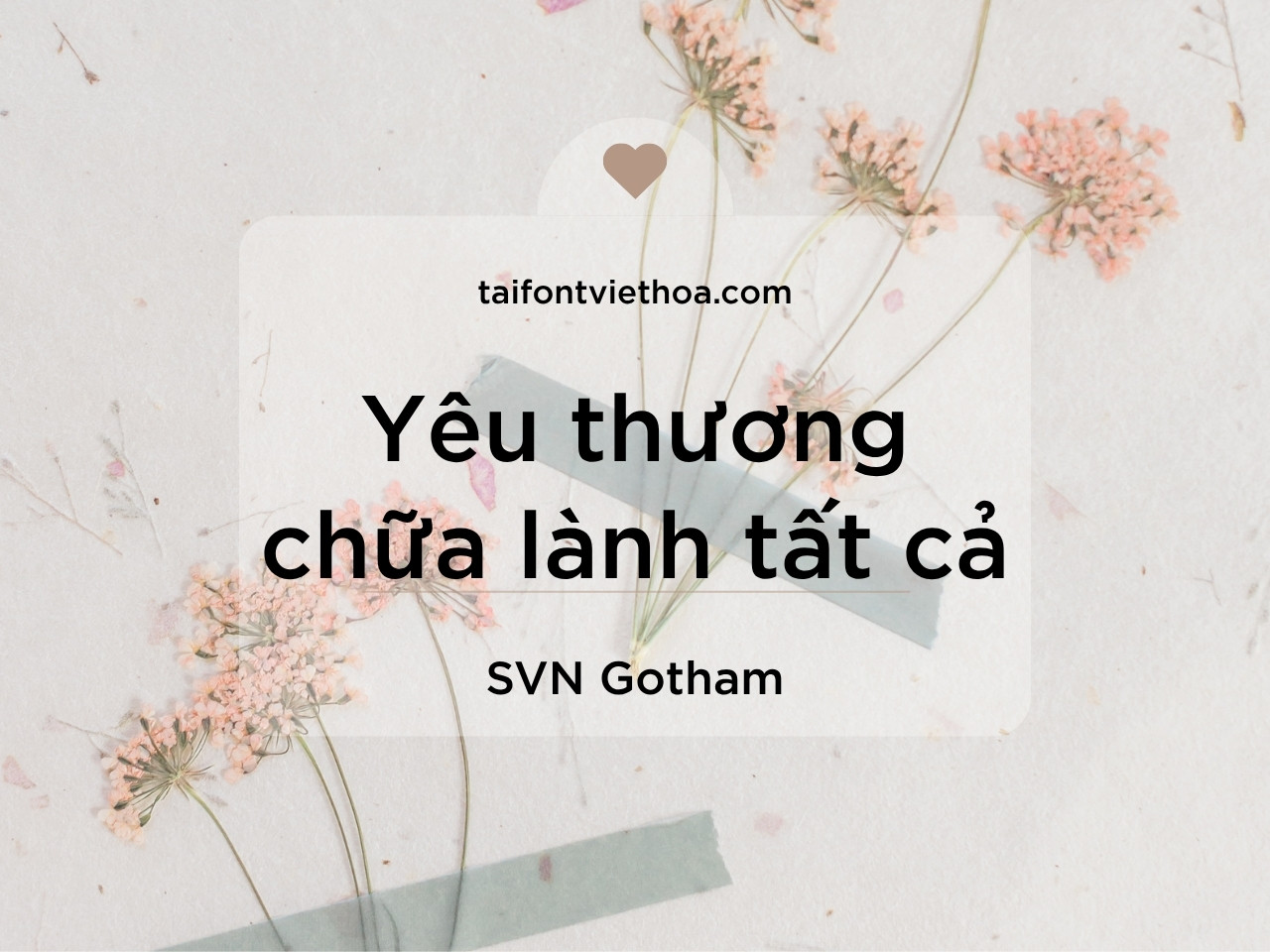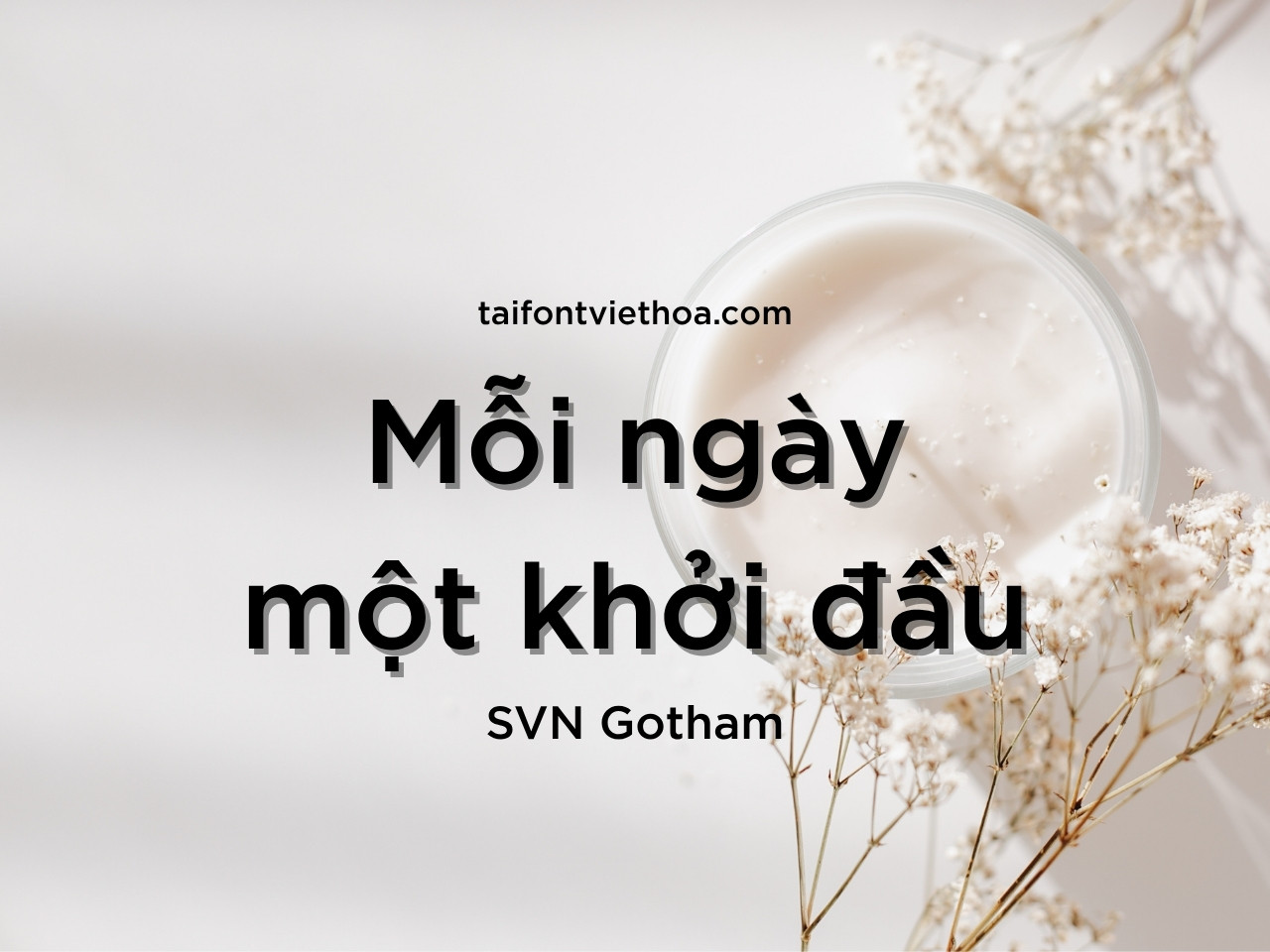
Font việt hóa SVN Gotham Sử Dụng Trong Logo TiKTok
Giới thiệu về font SVN Gotham – Kiểu chữ sans-serif hiện đại, phổ biến trong thiết kế thương hiệu
SVN Gotham là phiên bản Việt hóa của font Gotham – một trong những kiểu chữ sans-serif được sử dụng rộng rãi và phổ biến trong ngành thiết kế, đặc biệt trong các logo thương hiệu lớn như TikTok. Font được thiết kế với cấu trúc cân đối, hiện đại và dễ đọc, mang lại sự mạnh mẽ, chuyên nghiệp và tính nhận diện cao.
Phiên bản Việt hóa của SVN Gotham đã được Taifontviethoa.com chỉnh sửa kỹ lưỡng, hỗ trợ đầy đủ dấu tiếng Việt cùng hơn 70 ngôn ngữ khác. Font giúp các nhà thiết kế dễ dàng áp dụng trong các dự án thương hiệu đa dạng, giữ nguyên sự tinh tế và sắc nét của bản gốc.
Thiết kế sans-serif hiện đại – Ứng dụng rộng rãi trong logo và thương hiệu
SVN Gotham sở hữu cấu trúc sans-serif với các nét chữ dày, rõ ràng và cân đối, tạo cảm giác mạnh mẽ, chuyên nghiệp và dễ nhận diện. Font rất phù hợp cho các logo, tiêu đề, banner và các sản phẩm truyền thông cần sự nổi bật và tinh tế. Thiết kế của Gotham đặc biệt thích hợp với các thương hiệu công nghệ, truyền thông và mạng xã hội như TikTok.
Ứng dụng lý tưởng: thiết kế logo thương hiệu, banner quảng cáo, nhận diện thương hiệu số, giao diện người dùng và các dự án marketing sáng tạo. Ngành nghề phù hợp: công nghệ, truyền thông, giải trí, quảng cáo và thương mại điện tử.